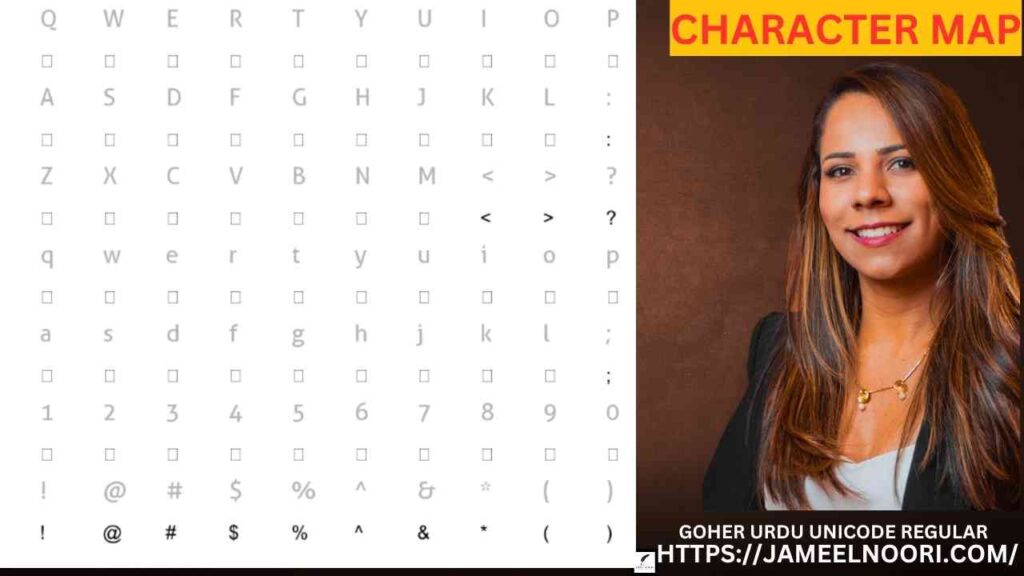
Agar aap Urdu typing ke liye ek stylish aur readable font dhoondh rahe hain, to Download Urdu font Goher Urdu Unicode Regular aap ke liye best choice ho sakta hai. Yeh font not only elegant hai, balkay compatible bhi hai Microsoft Word, InPage, aur Adobe software ke saath. Is article me hum is font ke download, features, compatibility, aur usage ka asaan tareeqa Roman Urdu me samjhayenge.
Download Urdu font Goher Urdu Unicode Regular ka Introduction
Download Urdu font Goher Urdu Unicode Regular ek classic aur Unicode-based Urdu font hai jo Urdu lovers aur designers ke liye specially design kiya gaya hai. Is font ki readability aur smooth curves ise logon mein popular banate hain.
- Stylish design for digital & print use
Download Urdu font Goher Urdu Unicode Regular ka Use kahan hota hai?
Yeh font commonly use hota hai:
- InPage aur MS Word me Urdu content likhne ke liye
- Posters aur flyers banane me
- Websites me decorative Urdu headings ke liye
- Social media posts ke Urdu captions me
Agar aap kisi professional ya educational project ke liye Urdu content tayar kar rahe hain, to Goher Urdu Unicode Regular aap ke liye best font hai.
Why Choose Goher Urdu Unicode Regular Font?
Agar aap soch rahe hain ke yeh font kyun choose karein, to yahan kuch strong reasons hain:
- ✅ Unicode hone ki wajah se easy compatibility
- ✅ Stylish aur professional appearance
- ✅ Lightweight aur fast performance
Tips for Better Usage of Goher Urdu Unicode Regular
- Combine karein isay dusre Nastaleeq fonts ke sath for modern designs
- Use karein high-resolution software jaise Adobe Illustrator for crisp output
Conclusion – Download Urdu font Goher Urdu Unicode Regular for Stylish Urdu Typing